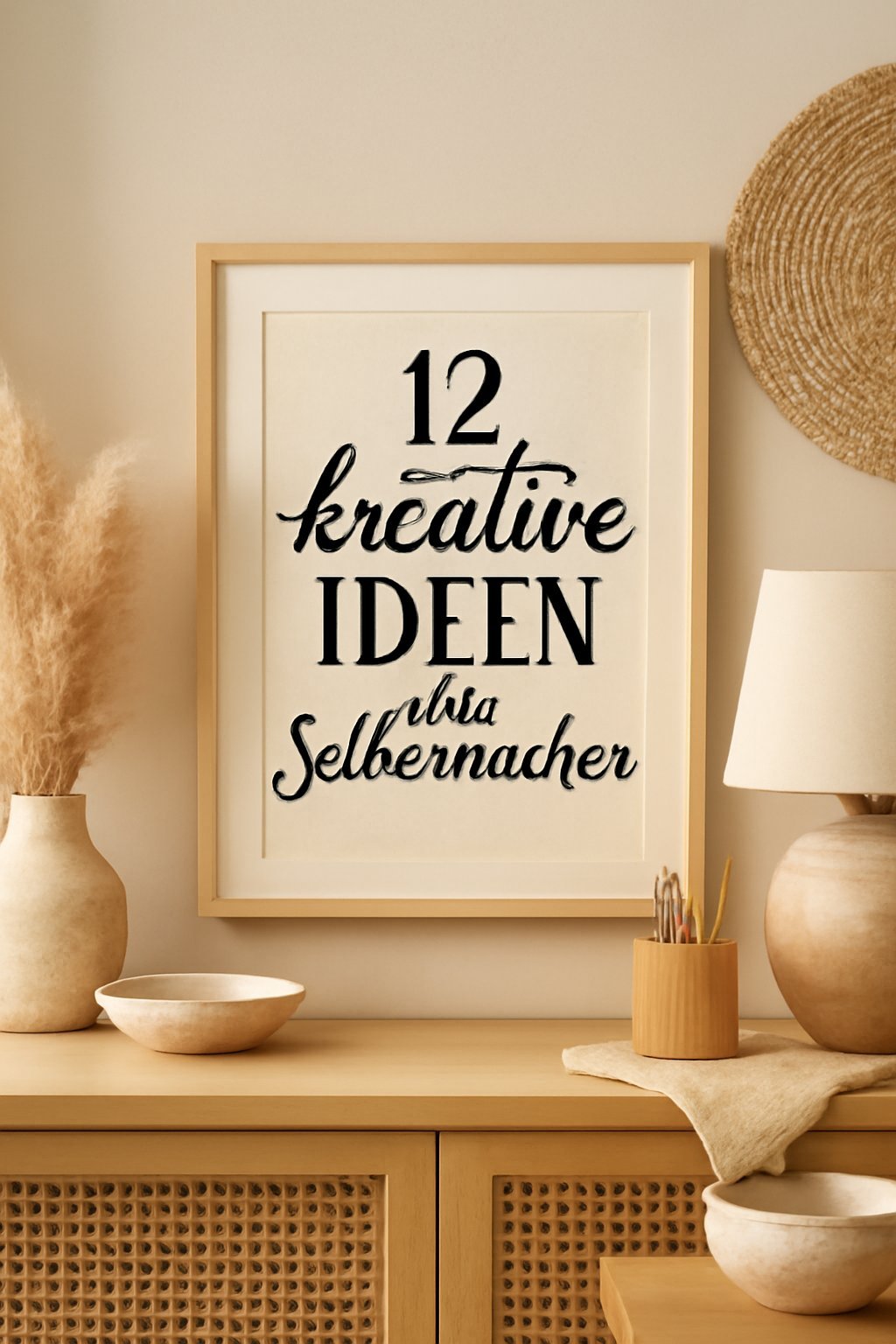
Merken Handlettering Schriftarten: 12 kreative Ideen zum Selbermachen
Warum Handlettering Schriftarten
Handlettering Schriftarten sind mehr als nur Buchstaben — sie sind eine kreative Ausdrucksform, die sich aus der traditionellen Kalligraphie entwickelt hat. Diese Kunst ermöglicht es dir, mit unterschiedlichen Techniken und Materialien einzigartige Schriftzüge zu kreieren, die sowohl Alltagsgegenstände als auch besondere Anlässe verschönern. Ob für Einladungen, Geschenkanhänger oder einfach nur zur Dekoration — die Möglichkeiten sind nahezu unbegrenzt und bieten dir einen persönlichen Spielraum, um deinen individuellen Stil auszudrücken. Bei der Auswahl von Handlettering Schriftarten solltest du auf verschiedene Aspekte achten. Die Form, die Dicke der Striche und die Eleganz der Buchstaben können die Stimmung und den Charakter deines Projekts stark beeinflussen. Aus verschiedenen Tutorials und Foren geht hervor, dass besonders sanfte, geschwungene Schriftarten oft als freundlich und einladend wahrgenommen werden, während klare, geradlinige Schriften mehr für Minimalismus und Modernität stehen. Es lohnt sich, mit verschiedenen Stilen zu experimentieren und zu sehen, welche Schriftarten am besten zu deinem Vorhaben passen. So kannst du nicht nur deinen Produkten das gewisse Etwas verleihen, sondern auch deine eigene Handschrift entwickeln.Handlettering Schriftarten: 12 kreative Ideen zum Selbermachen
- Bereite dein Skizzenbuch vor, indem du eine leere Seite auswählst. Lege die Vorlage für die Buchstaben daneben, um dir Inspiration zu holen.
- Beginne mit dem Zeichnen der Buchstaben. Nutze das Lineal, um gerade Linien zu ziehen und die Buchstaben gleichmäßig zu gestalten.
- Sobald du mit deinen Skizzen zufrieden bist, gehe mit den verschiedenen Stiften über die Bleistiftlinien.
- Verwende den feineren Stift für Details und Verzierungen. Füge Schattierungen oder Muster hinzu, um deinen Schriftzügen mehr Tiefe zu verleihen.
- Lass die Tinte gut trocknen, bevor du den Radiergummi benutzt, um die Bleistiftlinien zu entfernen. Dies verhindert, dass die Tinte verschmiert und dein Design ruiniert wird.
- Gestalte eine ganze Seite mit verschiedenen Buchstaben, um deine Fähigkeiten zu verbessern.
- Wenn du mit deinen Schriftzügen zufrieden bist, kannst du sie in deine Projekte einfügen oder sie als Geschenke verwenden.
- Bewahre deine Schriftzüge in einem sicheren Ort auf, damit sie nicht beschädigt werden. Du kannst sie in einem speziellen Ordner oder einer Mappe aufbewahren.
Gelingtipps
- Übe regelmäßig, um deine Fähigkeiten im Handlettering zu verbessern und sicherer zu werden.
- Halte deine Stifte gut gepflegt, damit sie immer die beste Leistung bringen.
- Nutze verschiedene Papiersorten, um unterschiedliche Effekte zu erzielen.
- Verwende ein gutes Skizzenbuch, um die besten Ergebnisse zu erzielen; es sollte dick genug sein, um das Durchdrücken der Tinte zu verhindern.
- Experimentiere mit verschiedenen Stiftspitzen, um eine Vielzahl von Strichstärken zu erreichen.
Aufbewahrung & Haltbarkeit
Die Schriftzüge sollten an einem trockenen Ort aufbewahrt werden, um Schäden zu vermeiden. Du kannst sie in einer Mappe für bis zu 6 Monate lagern. Wenn du sie einlaminierst, bleiben sie noch länger erhalten.
Variationsideen
- Kreative Farben: Nutze verschiedene Farbstifte oder Marker, um deinen Schriftzügen einen lebendigen Look zu verleihen.
- Verzierte Buchstaben: Füge kleine Zeichnungen oder Verzierungen um die Buchstaben herum hinzu, um sie interessanter zu gestalten.
- Große Buchstaben: Experimentiere mit großen Buchstaben, um auffällige Überschriften für deine Projekte zu erstellen.
Schritt 1
Bereite dein Skizzenbuch vor, indem du eine leere Seite auswählst. Lege die Vorlage für die Buchstaben daneben, um dir Inspiration zu holen. Achte darauf, dass der Untergrund stabil ist, damit du gut arbeiten kannst. Dies ist wichtig, damit du die Stifte gleichmäßig auftragen kannst und ein sauberes Ergebnis erhältst. Halte den Bleistift bereit, um die ersten skizzenhaften Entwürfe zu erstellen.
Schritt 2
Beginne mit dem Zeichnen der Buchstaben. Nutze das Lineal, um gerade Linien zu ziehen und die Buchstaben gleichmäßig zu gestalten. Achte darauf, dass du die Vorlage als Referenz nutzt, um die Proportionen der Buchstaben richtig zu erfassen. Halte den Bleistift leicht, damit du später einfacher radieren kannst. Lass deiner Kreativität freien Lauf und experimentiere mit verschiedenen Formen.
Schritt 3
Sobald du mit deinen Skizzen zufrieden bist, gehe mit den verschiedenen Stiften über die Bleistiftlinien. Beginne mit dem dicksten Stift, um die Konturen der Buchstaben nachzuziehen. Achte darauf, gleichmäßigen Druck auszuüben, damit die Linien klar und deutlich erscheinen. Dies sorgt für einen professionellen Look und lässt deine Buchstaben lebendig wirken.
Schritt 4
Verwende den feineren Stift für Details und Verzierungen. Füge Schattierungen oder Muster hinzu, um deinen Schriftzügen mehr Tiefe zu verleihen. Experimentiere mit verschiedenen Techniken, wie zum Beispiel das Überlagern von Farben oder das Hinzufügen von Punkten und Strichen, um deinen persönlichen Stil zu zeigen. Achte darauf, dass du nicht zu viele Details hinzufügst, damit die Buchstaben gut lesbar bleiben.
Schritt 5
Lass die Tinte gut trocknen, bevor du den Radiergummi benutzt, um die Bleistiftlinien zu entfernen. Dies verhindert, dass die Tinte verschmiert und dein Design ruiniert wird. Sei vorsichtig beim Radieren, um die Tinte nicht zu beschädigen. Dies ist ein wichtiger Schritt, um ein sauberes Endprodukt zu erhalten.
Schritt 6
Gestalte eine ganze Seite mit verschiedenen Buchstaben, um deine Fähigkeiten zu verbessern. Du kannst verschiedene Schriftarten ausprobieren und sehen, welche dir am besten gefällt. Dies ist eine tolle Übung, um deine Kreativität auszuleben und deinen persönlichen Stil zu entwickeln. Versuche, verschiedene Kombinationen und Anordnungen zu testen.
Schritt 7
Wenn du mit deinen Schriftzügen zufrieden bist, kannst du sie in deine Projekte einfügen oder sie als Geschenke verwenden. Überlege, wie du deine Schriftzüge in Karten, Einladungen oder anderen Bastelprojekten nutzen kannst. Dies gibt dem Ganzen eine persönliche Note und zeigt deinen kreativen Ausdruck.
Schritt 8
Bewahre deine Schriftzüge in einem sicheren Ort auf, damit sie nicht beschädigt werden. Du kannst sie in einem speziellen Ordner oder einer Mappe aufbewahren. So hast du immer einen Überblick über deine Arbeiten und kannst sie bei Bedarf wieder verwenden. Denke daran, regelmäßig neue Designs zu erstellen, um deine Fähigkeiten weiterzuentwickeln.
Häufige Fragen
Welche Stifte sind am besten für Handlettering?
Verwende spezielle Handlettering Stifte, die eine flexible Spitze haben und in verschiedenen Farben erhältlich sind.
Wie kann ich meine Schriftzüge aufbewahren?
Bewahre sie in einer Mappe auf, um sie vor Beschädigungen zu schützen. Laminieren verlängert die Haltbarkeit.
Kann ich Handlettering Schriftarten auch digital erstellen?
Ja, es gibt viele Apps und Programme, mit denen du Handlettering digital gestalten kannst.
Wie lange dauert es, um Handlettering zu lernen?
Es variiert, aber mit regelmäßigem Üben kannst du in wenigen Wochen Fortschritte machen.
Gibt es spezielle Papiersorten für Handlettering?
Ja, dickere Papiere sind ideal, um ein Durchdrücken der Tinte zu vermeiden und ein sauberes Ergebnis zu erzielen.